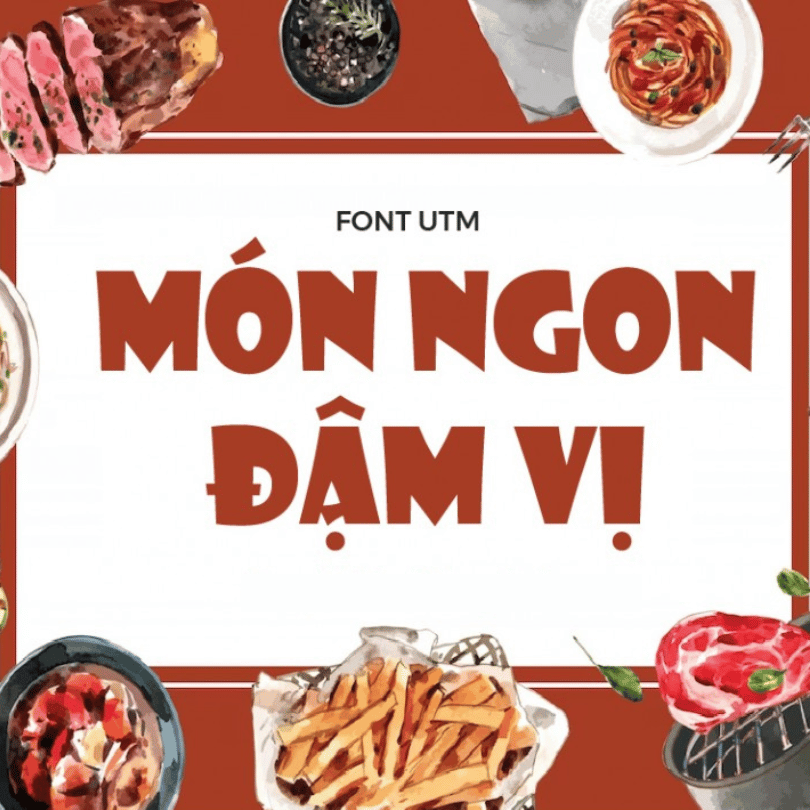
Việt hóa font UTM Showcard
Thông tin về font UTM Showcard
• UTM Showcard là một font chữ display (trang trí) có phong cách in đậm, góc cạnh, thường dùng cho tiêu đề, poster, thiết kế nổi bật.
• Font này thuộc bộ sưu tập của UTM (Urw Type Foundry) và có sẵn dạng free hoặc premium tùy phiên bản.
2. Việt hóa font UTM Showcard